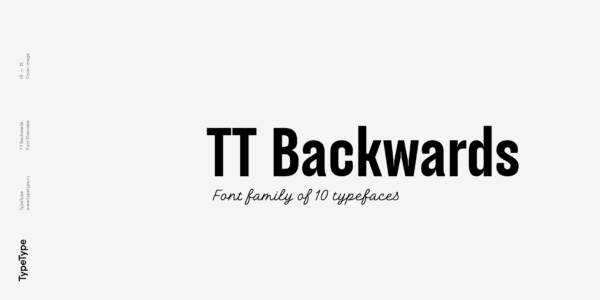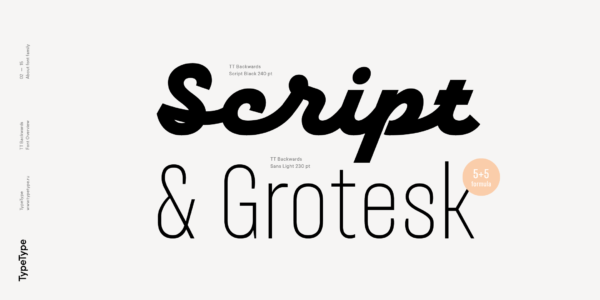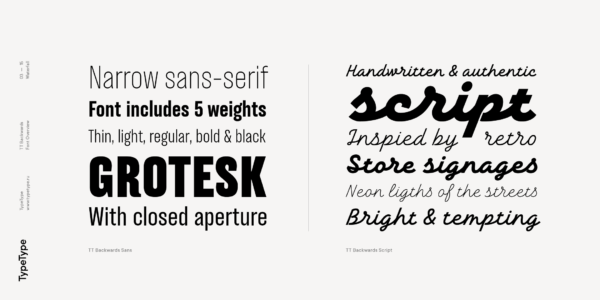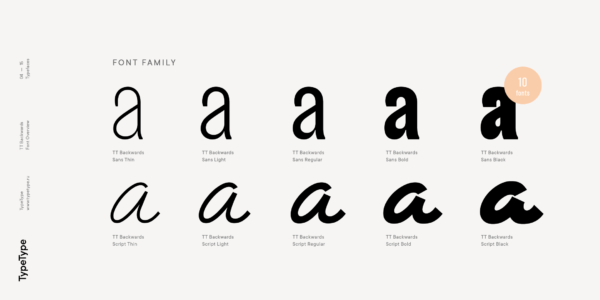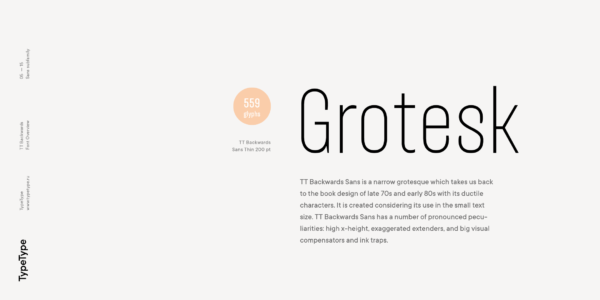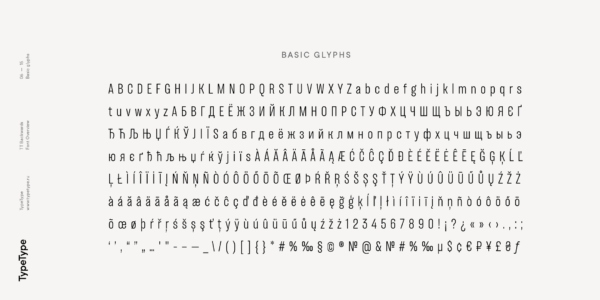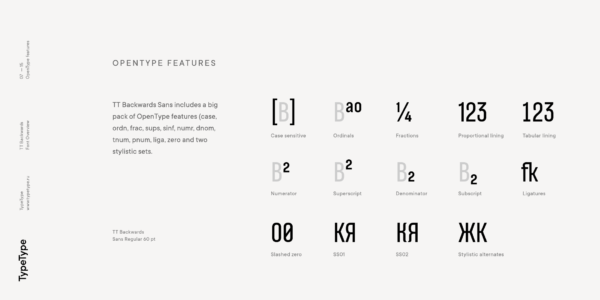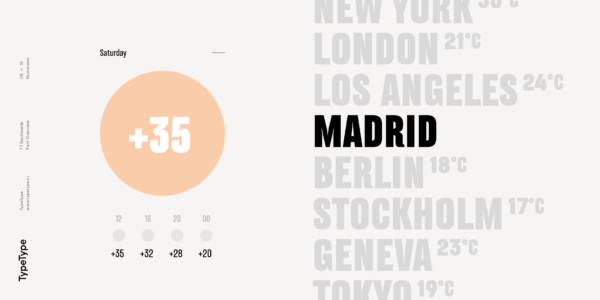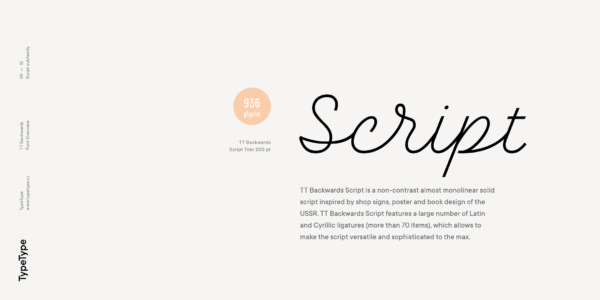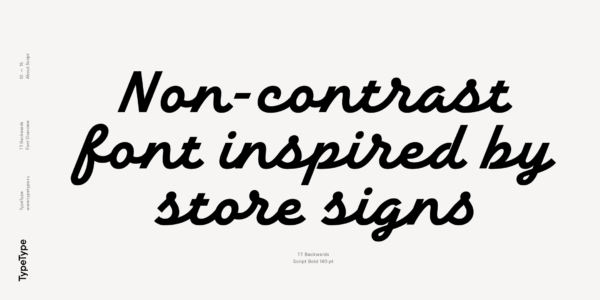
TT Backwards
TT Backwards — ТТ Бэквордс
Произносится «ТТ Бэквордс». «Backwards» в переводе с английского «назад». Буквы «TT» являются аббревиатурой названия компании.
TT Backwards — экспериментальная гарнитура, вдохновлённая типографикой CCCP конца 70-х — начала 80-х годов. Состоит из узкого пластичного гротеска и рукописного шрифта.
Узкий гротеск, вдохновленный книжным оформлением конца 70-х — начала 80-х годов
Магазинные вывески, постеры и плакаты, книжное оформление — вот где мы черпали вдохновение для нашего проекта. В TT Backwards Sans кроме базового стилистического решения присутствует два экспериментальных стилистических сета, которые достаточно сильно меняют общее визуальное восприятие текста. SS01 изменяет высокочастотные символы кириллицы, а SS02 сильно меняет высокочастотные символы латинского алфавита.
Проект вдохновлен магазинными вывесками, а также плакатным и книжным оформлением в CCCP
TT Backwards состоит из двух шрифтовых подсемейств: гротеска и скрипта
TT Backwards Script
TT Backwards в дизайне
О гарнитуре TT Backwards
TT Backwards — это экспериментальный шрифтовой проект, вдохновлённый типографикой и шрифтами CCCP конца 70-х и начала 80-х годов. Магазинные вывески, постеры и плакаты, книжное оформление — вот где мы черпали вдохновение для нашего проекта. TT Backwards состоит из двух комплементарных шрифтовых подсемейств: гротеска и скрипта, в каждое из которых входит по 5 начертаний в 5 разных весах (Thin, Light, Regular, Bold, Black).
TT Backwards Sans — это узкий гротеск, пластичностью своих знаков отсылающий нас в книжное оформление конца 70-х — начала 80-х годов и выполненный с учетом использования в маленьком размере текста. В TT Backwards Sans есть ряд ярко выраженных особенностей: высокий уровень x-heigth, гипертрофированные выносные элементы, большие визуальные компенсаторы и ловушки для краски.
В TT Backwards Sans кроме базового стилистического решения присутствует два экспериментальных стилистических сета, которые достаточно сильно меняют общее визуальное восприятие текста. SS01 изменяет высокочастотные символы кириллицы, а SS02 сильно меняет высокочастотные символы латинского алфавита. В TT Backwards Sans используются следующие OpenType фичи: case, ordn, frac, sups, sinf, numr, dnom, tnum, pnum, liga, zero, salt, ss01, ss02.